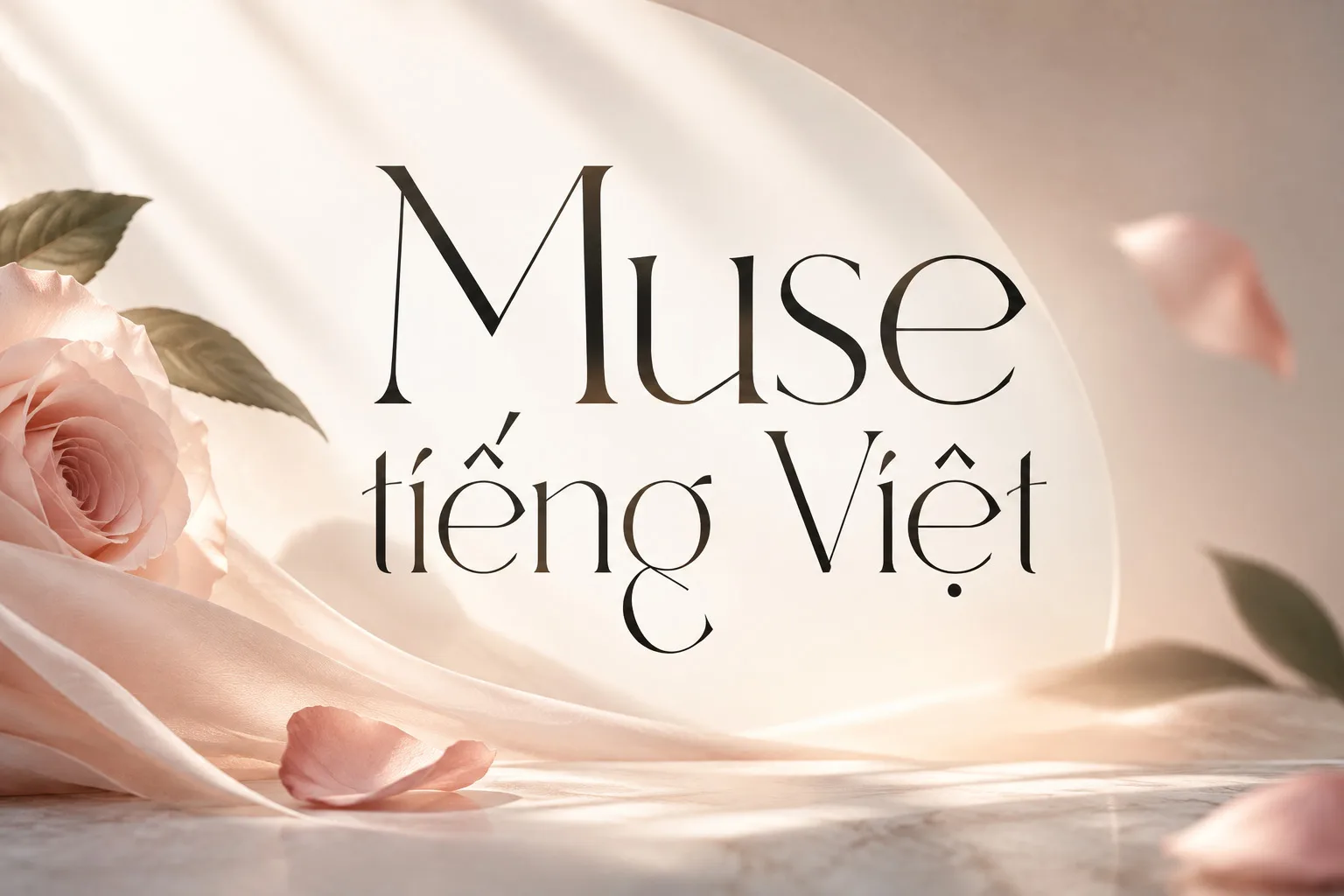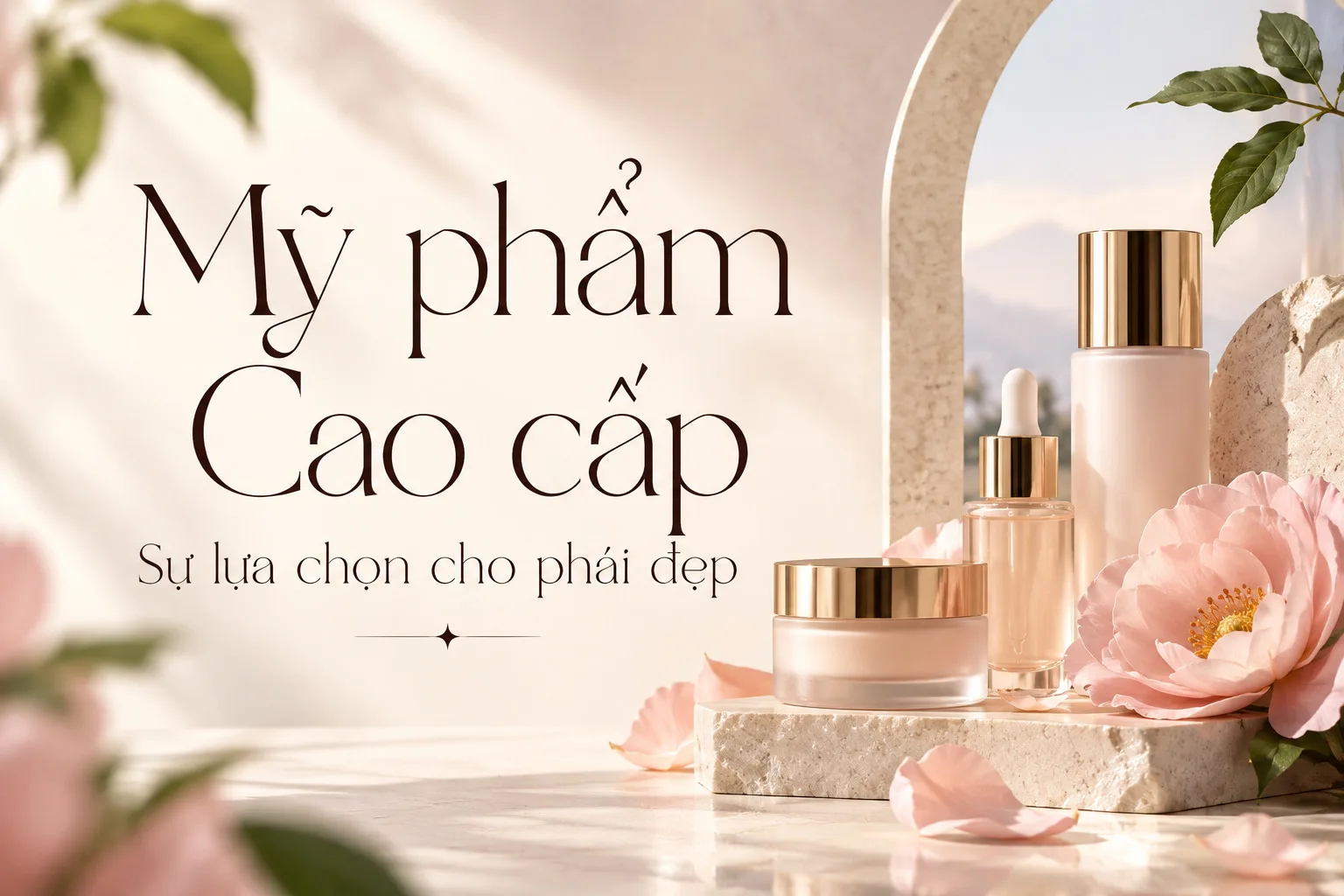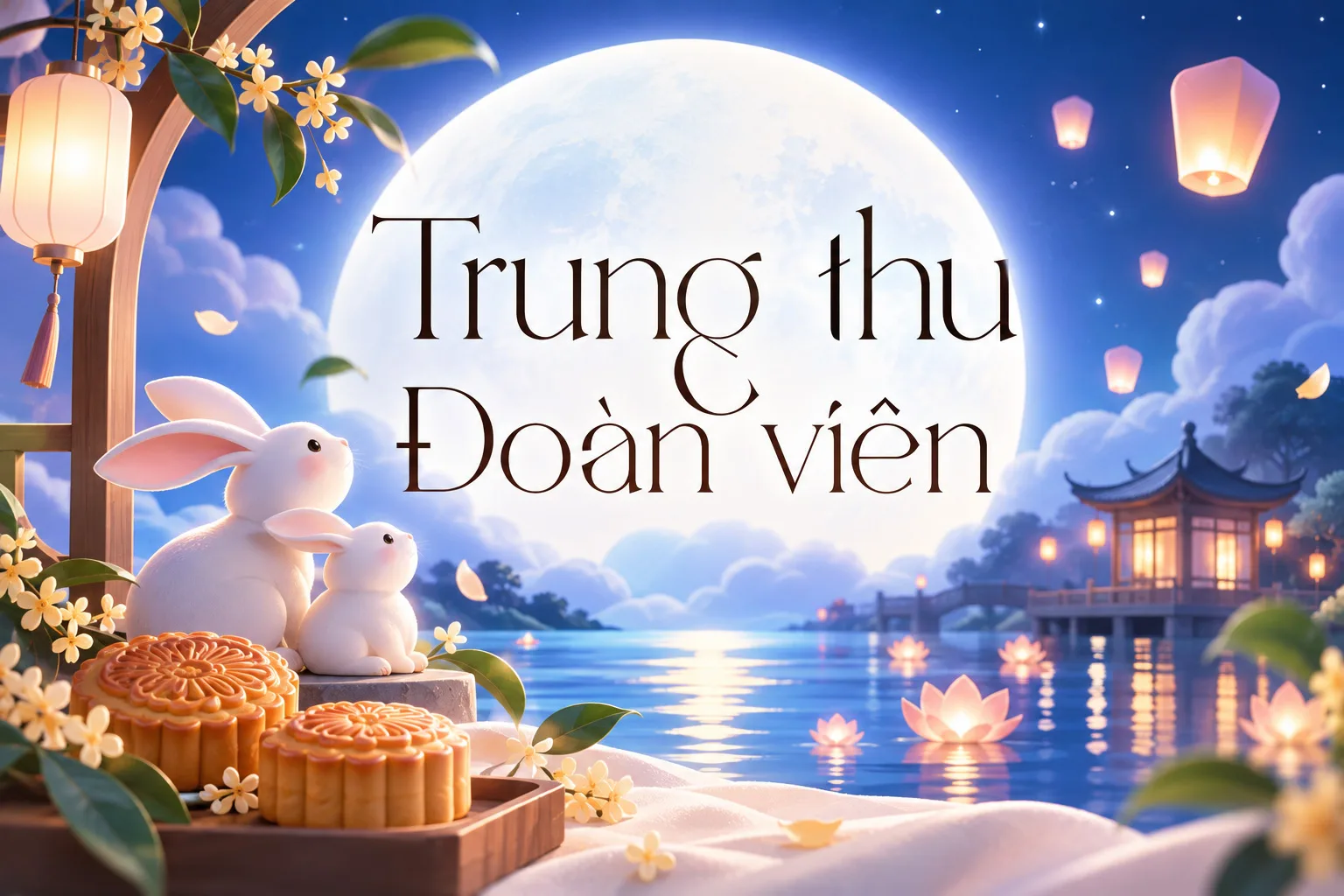
DVN Muse tiếng Việt – Font Serif Thanh Lịch, Nghệ Thuật & Đầy Cảm Hứng
DVN Muse là kiểu chữ Serif nghệ thuật mang vẻ đẹp thanh mảnh, tinh tế và đầy cảm hứng. Sở hữu độ tương phản cao giữa những nét chữ đậm và mảnh, kết hợp cùng các đường cong mềm mại và hình dáng ký tự độc đáo, DVN Muse tạo nên phong cách thị giác sang trọng, hiện đại và đậm chất thời trang.
Lấy cảm hứng từ những thiết kế typography cao cấp, DVN Muse đặc biệt phù hợp với các dự án yêu cầu sự thanh lịch, cá tính và tính thẩm mỹ cao. Từ logo thương hiệu, bìa tạp chí, poster nghệ thuật đến bao bì mỹ phẩm, thiệp cưới và các ấn phẩm thời trang, font chữ mang đến điểm nhấn ấn tượng cho mọi bố cục.
Với những đường nét thanh thoát và phong cách Display Serif nổi bật, DVN Muse không chỉ đơn thuần là một kiểu chữ mà còn là công cụ giúp truyền tải cảm xúc, tạo dựng dấu ấn riêng và nâng tầm chất lượng thiết kế.
Đặc điểm nổi bật
• Serif tương phản cao với nét thanh mảnh, sang trọng.
• Hình dáng ký tự mềm mại, giàu tính nghệ thuật.
• Phù hợp với phong cách thời trang, editorial và thương hiệu cao cấp.
• Ứng dụng đa dạng trong thiết kế logo, poster, tạp chí, mỹ phẩm và thiệp cưới.
DVN Muse – Nơi từng đường nét chữ trở thành nguồn cảm hứng sáng tạo.